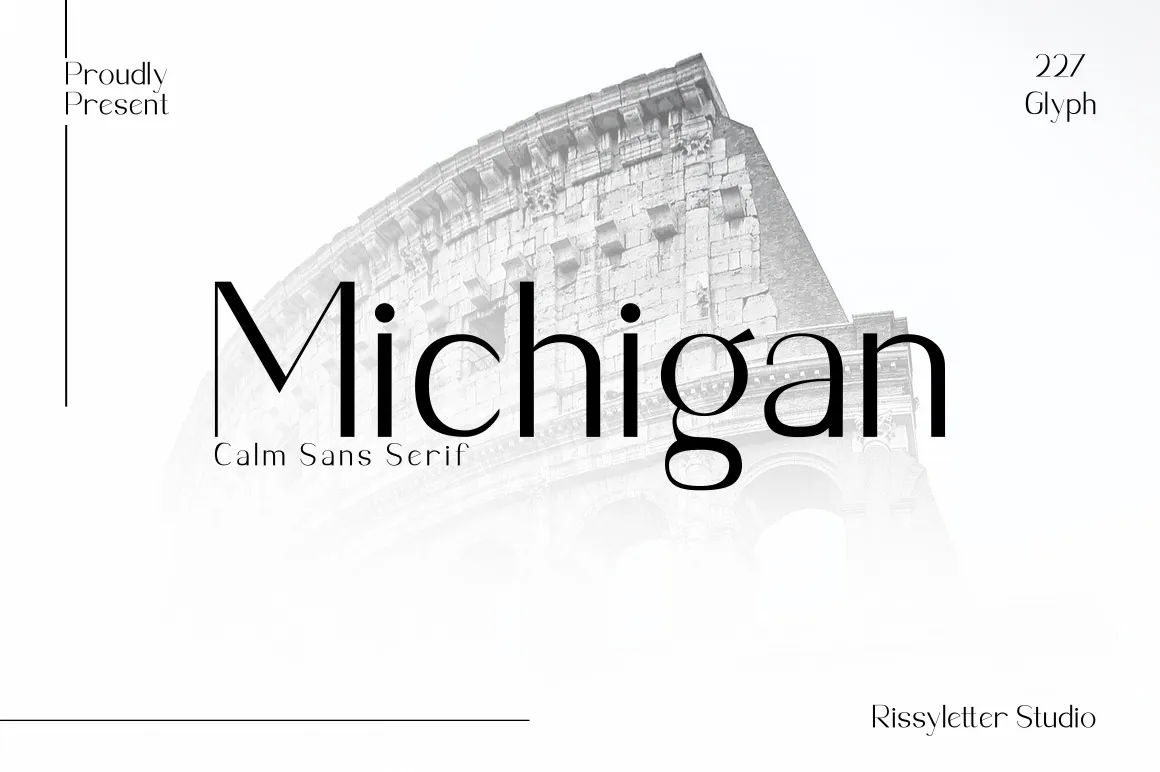
A Michigan Font é uma elegante fonte sans serif que oferece um toque romântico em cada curva com sua borda suave. Esta fonte está pronta para combinar perfeitamente com uma ampla variedade de projetos, tornando-a a escolha perfeita para quem busca uma identidade visual moderna e atraente. Seja você um designer gráfico inovador ou criativo, esta fonte será seu aliado ideal, adicionando um toque único que destaca seus trabalhos. Inclua Michigan Font em suas ideias de design e observe como ela as torna realmente especial.